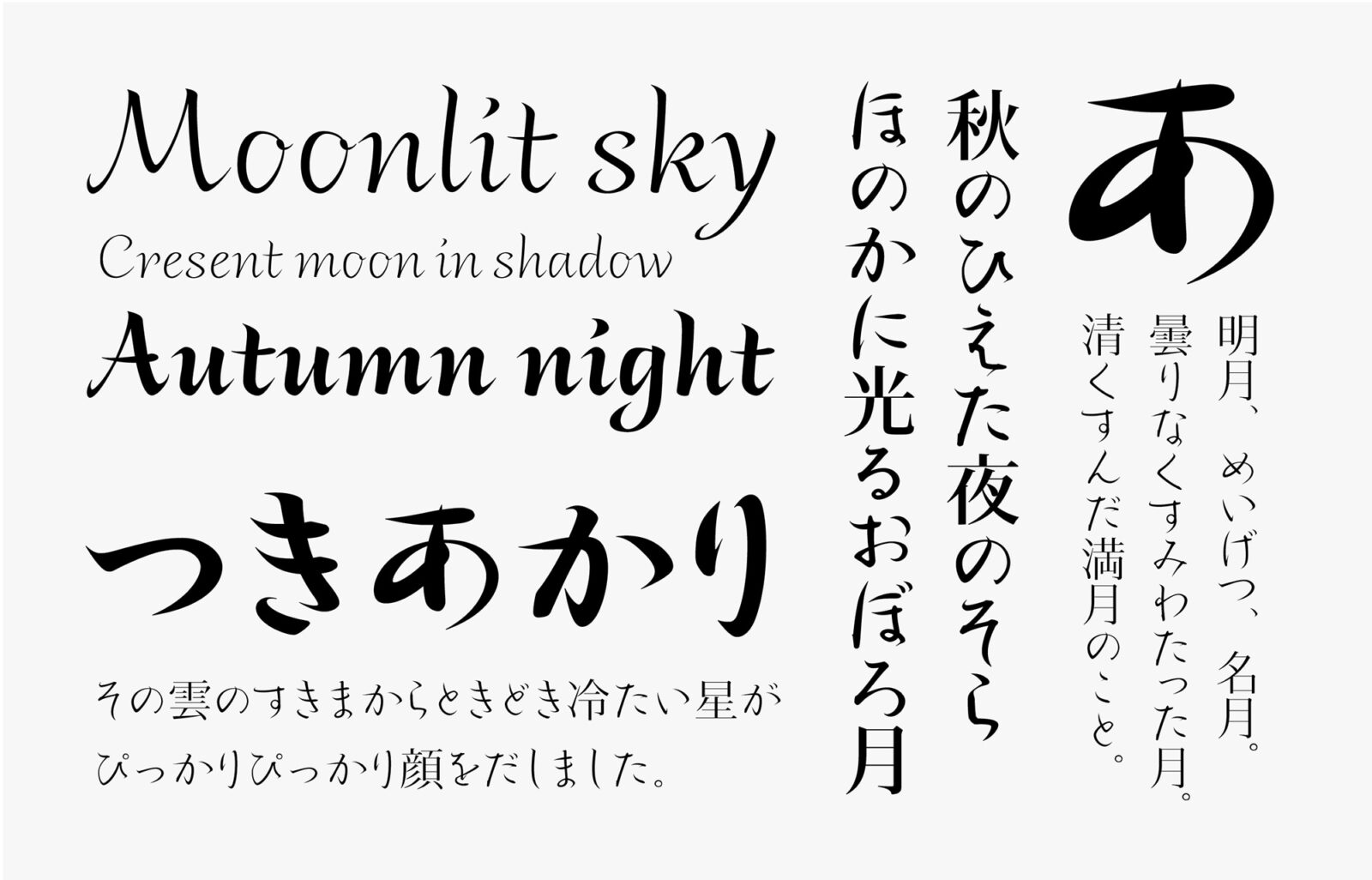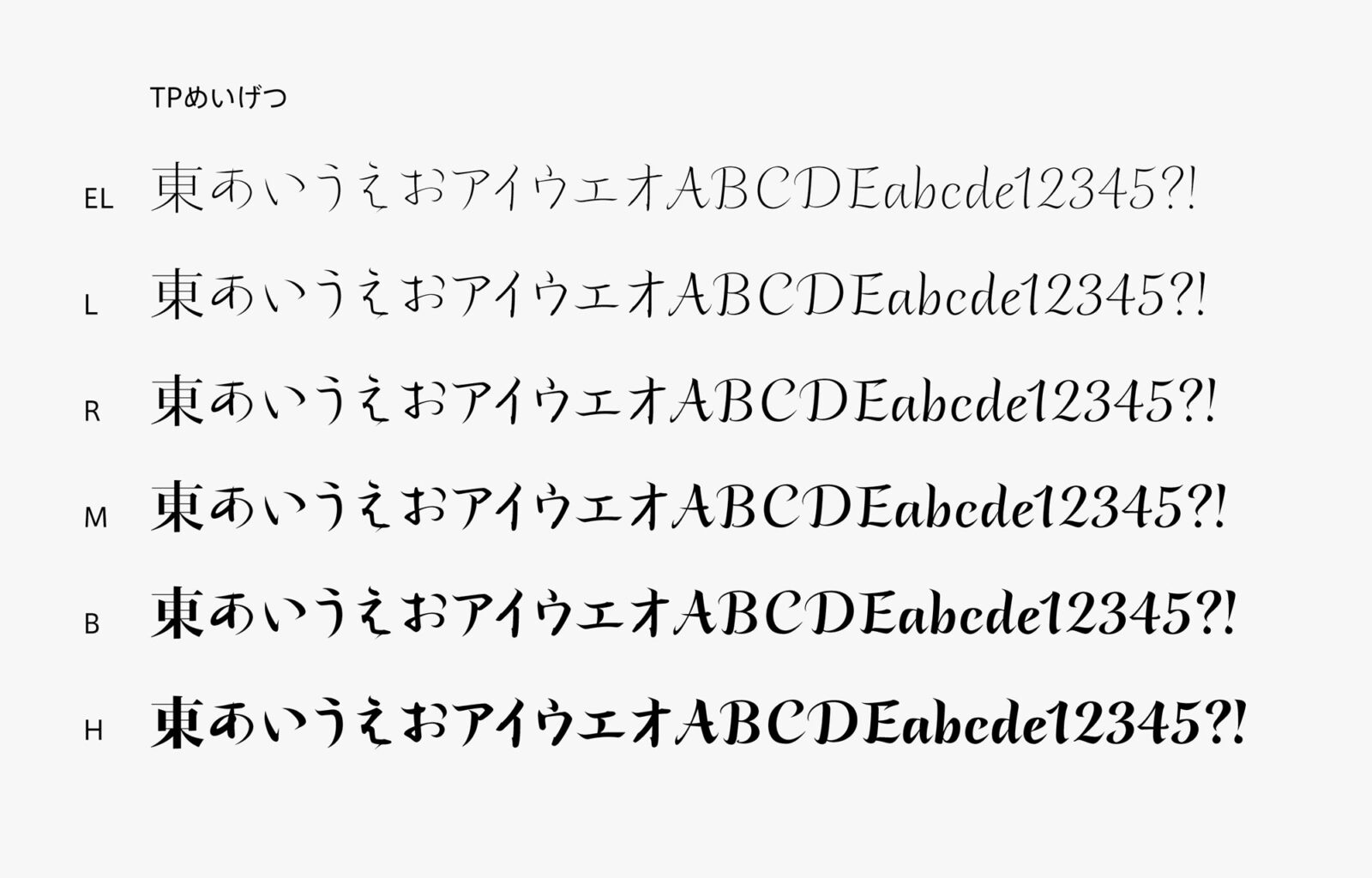
タイププロジェクト、四季フォントプロジェクト第二弾 「TPめいげつ」の提供を開始
藤原定家の筆跡を現代風にアレンジし、秋の澄んだ空に映える月をイメージした書体
タイププロジェクト株式会社(東京都練馬区 代表取締役社長 鈴木 功)は、四季フォントプロジェクトの第二弾として、秋の月を主題とした「TPめいげつ」を発表しました。本日よりタイププロジェクトのサブスクリプションサービス「TPコネクト」にて提供を開始いたします。四季フォントシリーズは、さまざまな時代の古典に学び、広く世界の文化・芸術からエッセンスを吸収し、現代に適した新しい書体を提案します。
TPめいげつは、藤原定家の個性味あふれる筆跡を現代風にアレンジしています。定家の文字は、ひときわ字面が大きくフトコロが広い点が特徴です。その特徴を活かした仮名と欧文を新しく開発し、TP明朝ハイコントラストの漢字を合わせています。漢字と仮名の取り合わせ、和文と欧文の掛け合い・響き合いは、四季フォントの見どころのひとつとなっています。
平仮名では、鋭く入る起筆から太い終筆に至るメリハリのきいたストロークと定家様の大きな特徴である扁平気味の独特なフォルムを明確に表現しています。カタカナは、定家の自筆「源氏物語 奥入」を手本にしています。また、定家様に調和するラテン文字を新たに書き起こし、月光を想わせる雰囲気のあるスクリプト体に仕上げました。
タイププロジェクトの代表取締役 鈴木 功は、「広く世界の歴史に関心をもち、風物自然を背景にした固有の文化を知ること、そしてその時代に独自な様式とさまざまな芸術に深く学ぶことが、四季フォントの基本姿勢です。『TPめいげつ』の名は、藤原定家が 56 年にわたって書き綴った日記『明月記』から採りました。幾多の古典を書き写し後代に伝えた定家に敬意を表し、韻文と散文の架け橋となるような書体を目指しました」と述べています。
優美繊細な古筆が多いなかで太いウエイトをカバーできる珍しい存在である TPめいげつは、鋭い印象のハイコントラストを軸に、EL (エクストラライト)から H (ヘヴィ)まで、6 つのウエイトで構成しています。